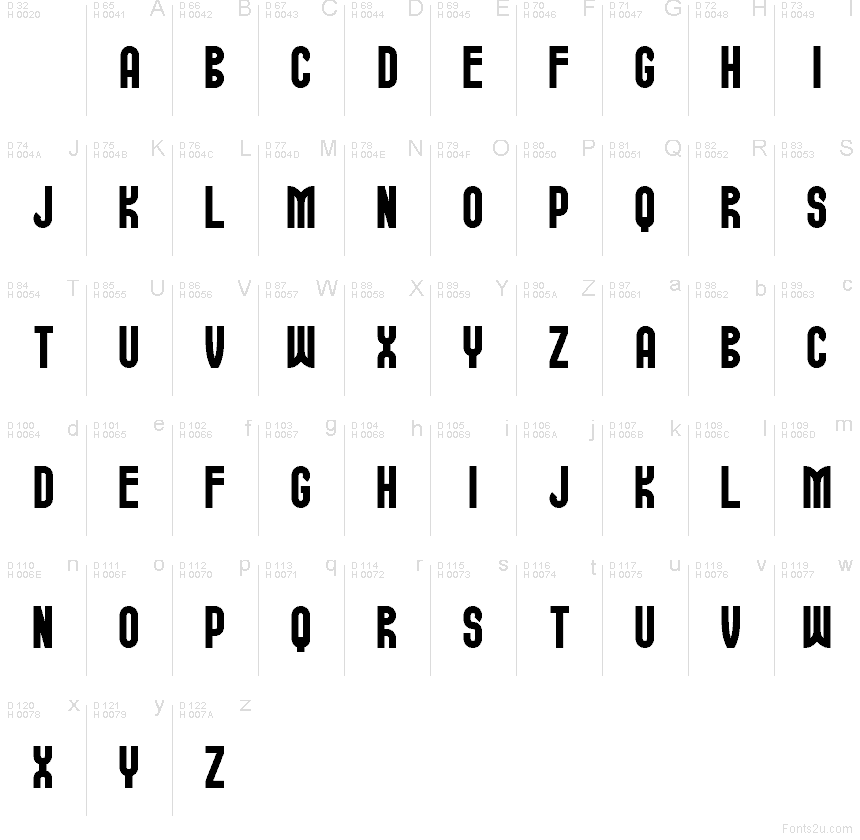
Broadcaster Elegant autorstwa Vladimira Nikolica to darmowy krój pisma typu display w stylu retro, z dużymi, zaokrąglonymi wielkimi literami i eleganckim klimatem epoki telewizji. Litery są zwarte i pewnie proste, z wysokimi pionowymi kształtami, miękkimi narożnikami i wyciętymi przestrzeniami wewnętrznymi, co nadaje krojowi płynny, plakatowy rytm.
Świetnie pasuje do plakatów muzycznych, okładek magazynów, kart tytułowych, brandingu i krótkich nagłówków na opakowaniach, gdzie te zwarte, rzeźbiarskie formy mogą udźwignąć cały wiersz tekstu. Jako darmowy font, sprawdzi się również w monogramach i inicjałach, ponieważ wielkie litery mają wystarczającą prezencję, by wyróżniać się w bardzo krótkich kompozycjach bez potrzeby dodatkowych ozdobników.